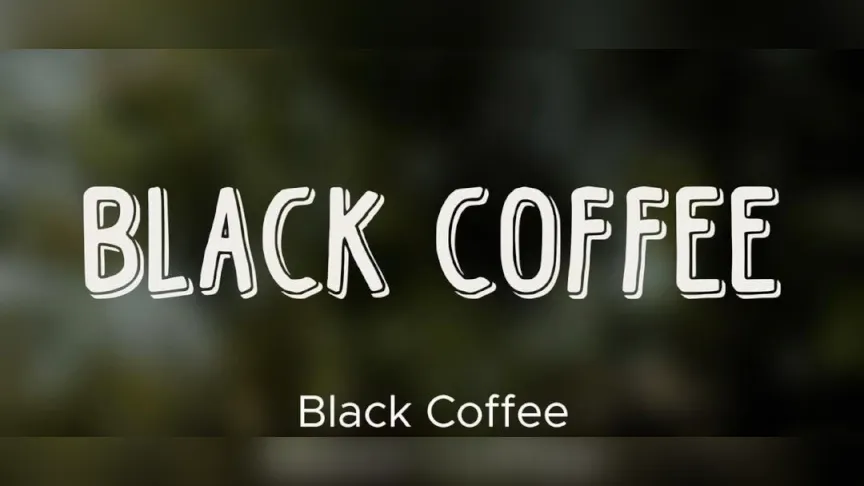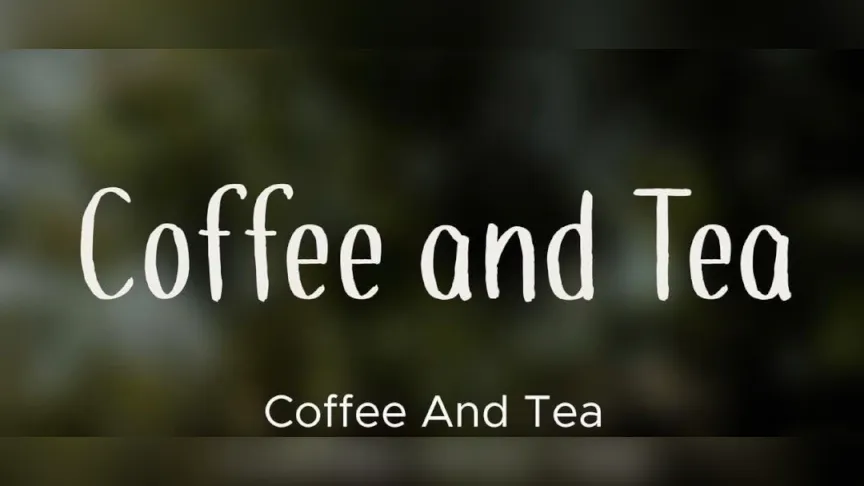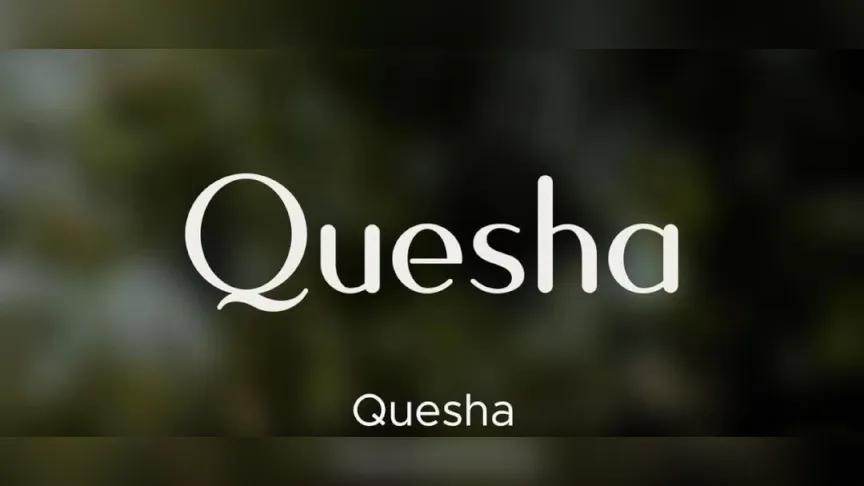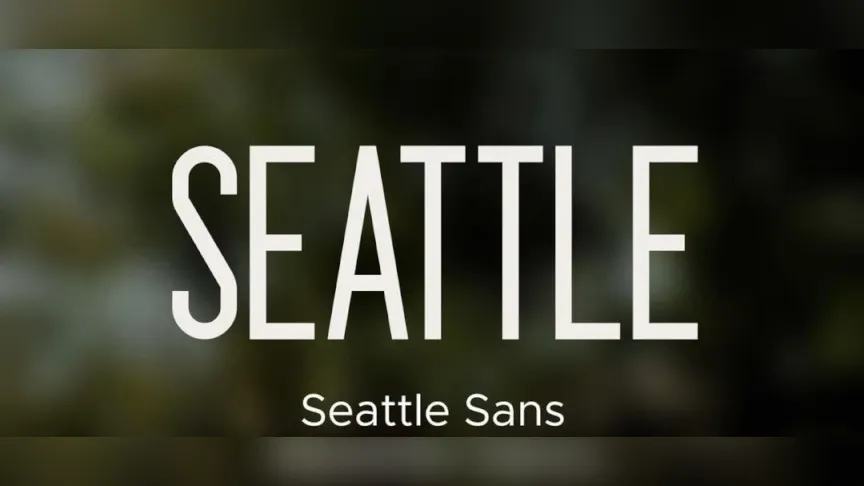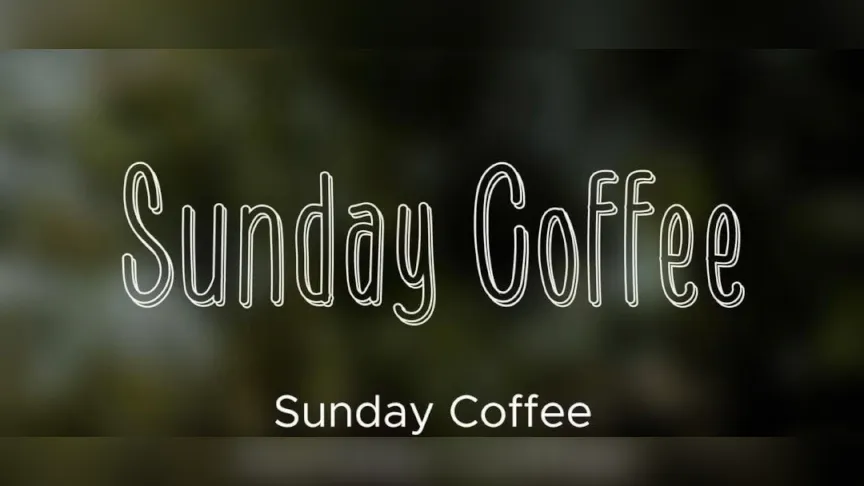
5 Rekomendasi Font yang Cocok untuk Coffee Shop
Rekomendasi font untuk desain, pamflet, promosi warung kopi atau bran identity coffe shop.
5 Rekomendasi Font yang Cocok untuk Coffee Shop
Membuka coffee shop bukan hanya soal racikan kopi yang nikmat, tetapi juga tentang cara menciptakan suasana yang hangat dan estetik. Salah satu elemen penting dalam branding sebuah warung kopi adalah pemilihan font. Font yang tepat dapat menciptakan kesan ramah, elegan, sekaligus khas bagi sebuah coffee shop.
Berikut adalah rekomendasi font yang bisa Anda gunakan untuk logo, menu, hingga desain interior digital coffee shop Anda:
1. Black Coffee
Black Coffee
Font ini memiliki karakter yang tebal (bold) dan berkesan retro, cocok untuk logo utama coffee shop. Garisnya yang tegas dengan sentuhan artistik membuatnya mudah terbaca. Black Coffee akan menonjolkan kesan vintage dan otentik, seolah membawa pengunjung pada suasana kedai kopi klasik.
2. Coffee And Tea
Coffee And Tea
Dengan gaya tulisan kuas (brush script) yang terlihat santai dan personal, font ini sangat cocok untuk desain papan menu, poster promo, atau kemasan. Karakternya yang kasual mampu menciptakan nuansa hangat dan akrab bagi para pelanggan.
3. Quesha
Quesha
Quesha hadir dengan desain yang elegan dan klasik. Font serif ini pas untuk coffee shop yang ingin memberikan kesan mewah dan berkelas. Sangat cocok digunakan untuk branding utama atau pada menu yang ingin menonjolkan kualitas premium.
4. Seattle
Seattle
Seattle adalah font sans-serif yang simpel dan clean, terinspirasi dari gaya tipografi modern perkotaan. Cocok dipakai untuk coffee shop dengan konsep urban, industrial, atau kontemporer. Dengan huruf yang bersih dan profesional, font ini pas untuk signage, menu digital, hingga label produk.
5. Sunday Coffee
Sunday Coffee
Font ini punya gaya tulisan tangan (handwritten) yang ringan dan personal, seolah menyerupai goresan di buku catatan. Sunday Coffee sangat cocok untuk coffee shop yang ingin menonjolkan kesan homey, hangat, dan bersahabat (friendly). Font ini bisa dipakai pada menu kafe, dekorasi dinding, hingga unggahan media sosial.
Pemilihan font untuk coffee shop bukan hanya soal estetika, tapi juga tentang membangun identitas jenama (brand). Dari yang tegas dan retro seperti Black Coffee, hingga yang hangat dan personal seperti Sunday Coffee, setiap font memiliki keunikannya sendiri.
Dengan menggunakan font yang tepat, coffee shop Anda tidak hanya akan dikenal lewat aroma kopinya, tetapi juga lewat identitas visual yang kuat.